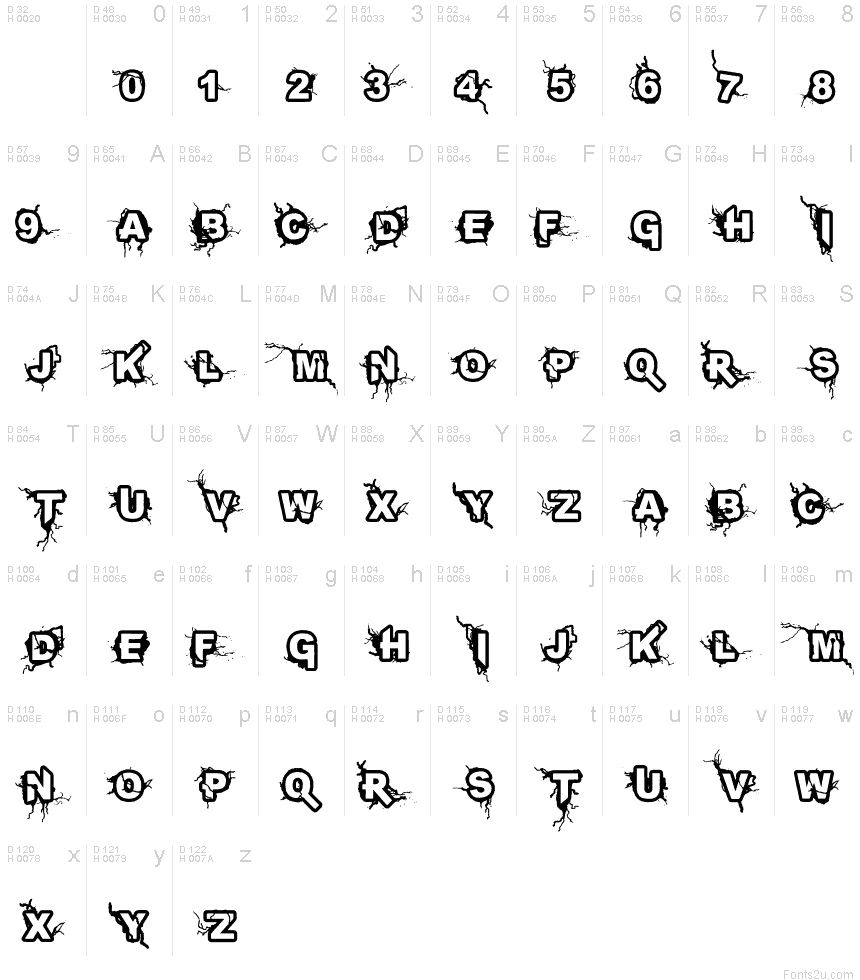
Infected è un font da display usurato e gratuito, costruito a partire da pesanti maiuscole contornate. Le sue forme a blocchi smussati sono scheggiate e rotte da aperture frastagliate. Viticci e schizzi simili a inchiostro si estendono oltre le lettere.
I segni ramificati si abbinano direttamente alle illustrazioni horror, trasformando un titolo in parte dell'opera d'arte. Sono inoltre adatti per copertine di album, grafica di videogiochi e poster per eventi di Halloween con un tema infetto o infestato. In questi utilizzi, le sagome danneggiate e le estensioni striscianti fanno sì che le lettere ricordino un oggetto contaminato piuttosto che una tipografia pulita.